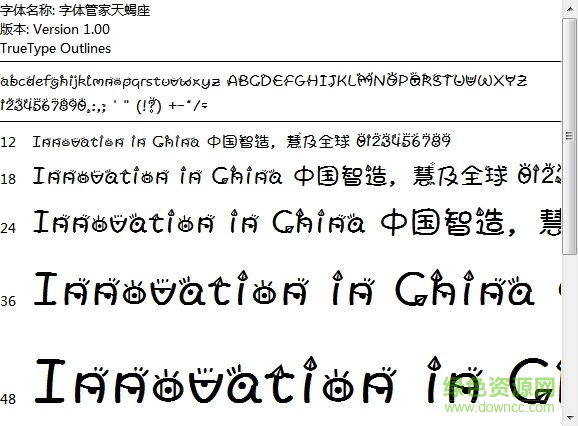
天蝎座字體包括奇思黑體天蝎座體、字體管家天蝎座和華康神秘天蠍體三款,每款字體各有其特色,或端正或卡通或飄逸,讓天蝎座的朋友可以有多重選擇,快來綠色資源網(wǎng)體驗(yàn)吧!
天蝎座字體是以胖丫為打底字,一雙極其敏銳的眼睛,能洞察人的弱點(diǎn)和機(jī)遇的利弊。具有神秘、好斗、狂熱和不妥協(xié)的精神。給人一種酷酷的帥氣,所以用牟釘、眼睛來作為打底字的裝飾,而形成的一款美化字體。
奇思黑體天蝎座體和字體管家天蝎座字體,均有著可愛的圖案點(diǎn)綴和修飾,給文字更加清新的視覺呈現(xiàn),而aa天蝎體沿用了同類星座字體的特色,文風(fēng)上保持一致,大家可下載兩款字體,選擇使用!